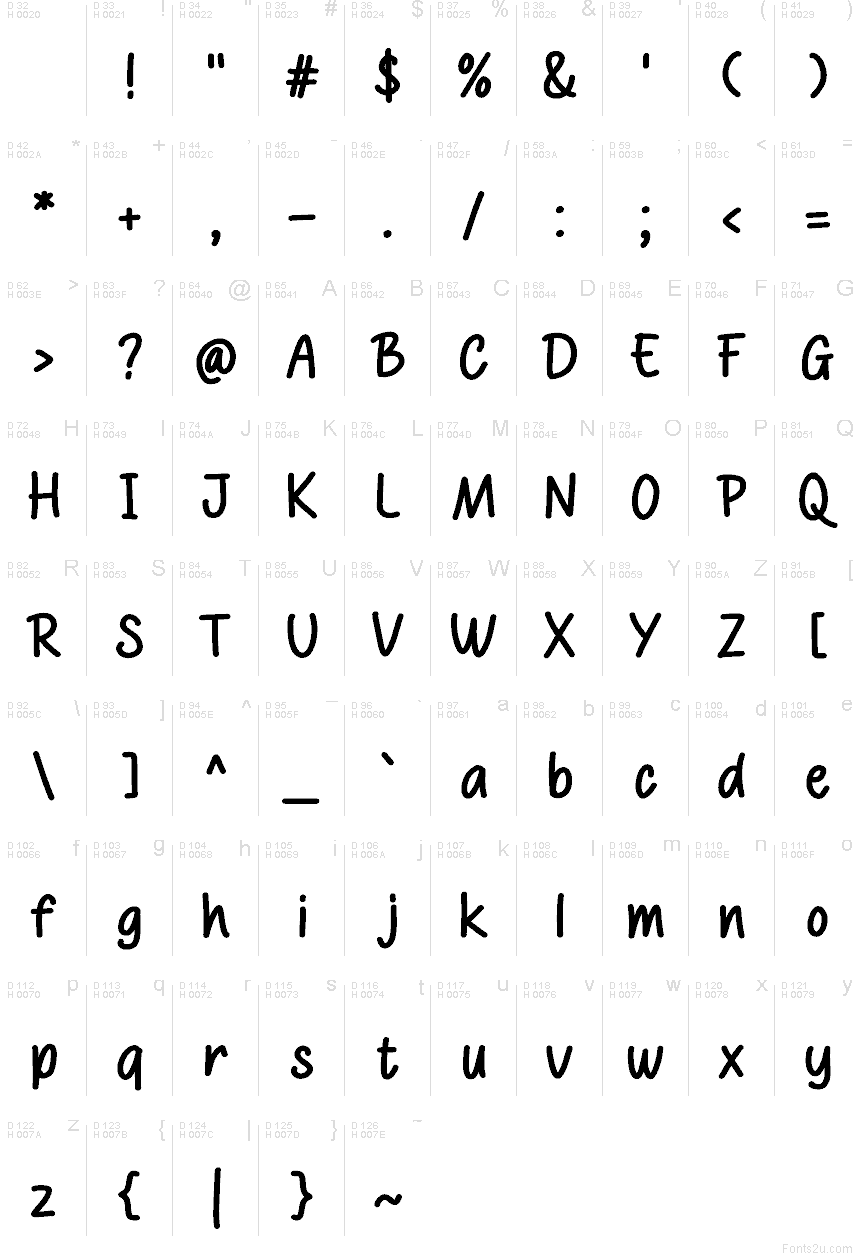
Holiday Ending هو خط يدوي مجاني يتميز بضربات دائرية وإيقاع مريح وغير منتظم قليلاً. تتميز أشكال الحروف بالبساطة والانفتاح، مع منحنيات ناعمة تضفي على التصميم طابعاً شخصياً وغير رسمي دون الحاجة إلى زخارف إضافية.
يعمل خط Holiday Ending بشكل رائع مع بطاقات المعايدة، ودعوات الأعياد، ورسومات وسائل التواصل الاجتماعي، وتنسيقات الاقتباسات، ونصوص الشعارات القصيرة حيث تكون لمسة الكتابة اليدوية أكثر فائدة من الأسلوب الرسمي. كما يتناسب هذا الخط المجاني مع ملصقات التغليف واللافتات الاحتفالية، لأن أشكاله المرنة تحافظ على دفء الرسالة ومباشرتها.